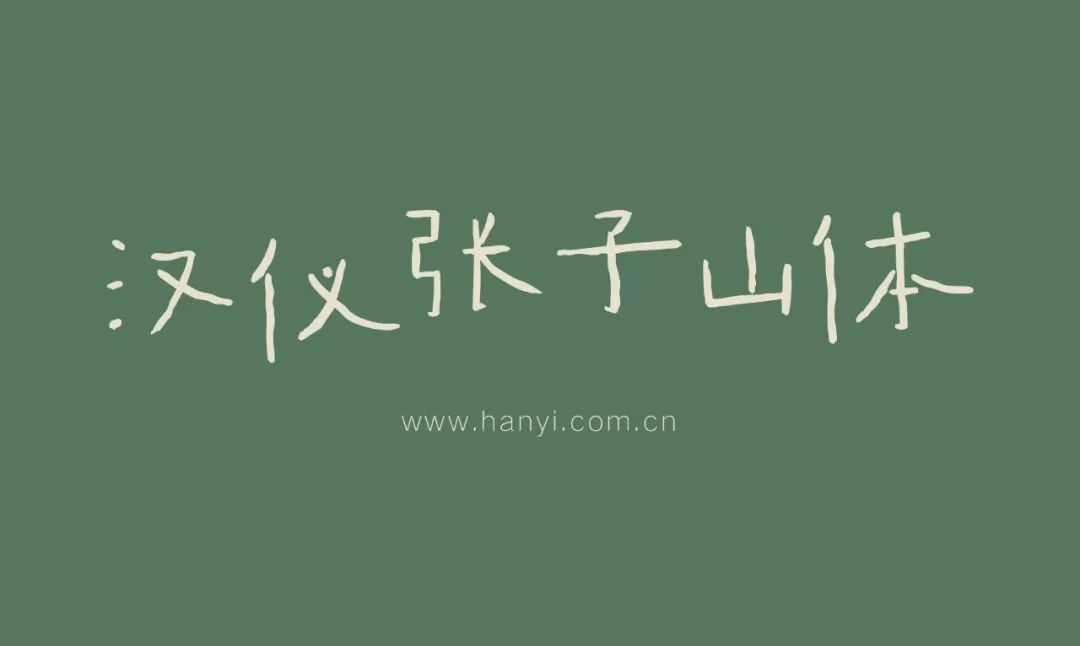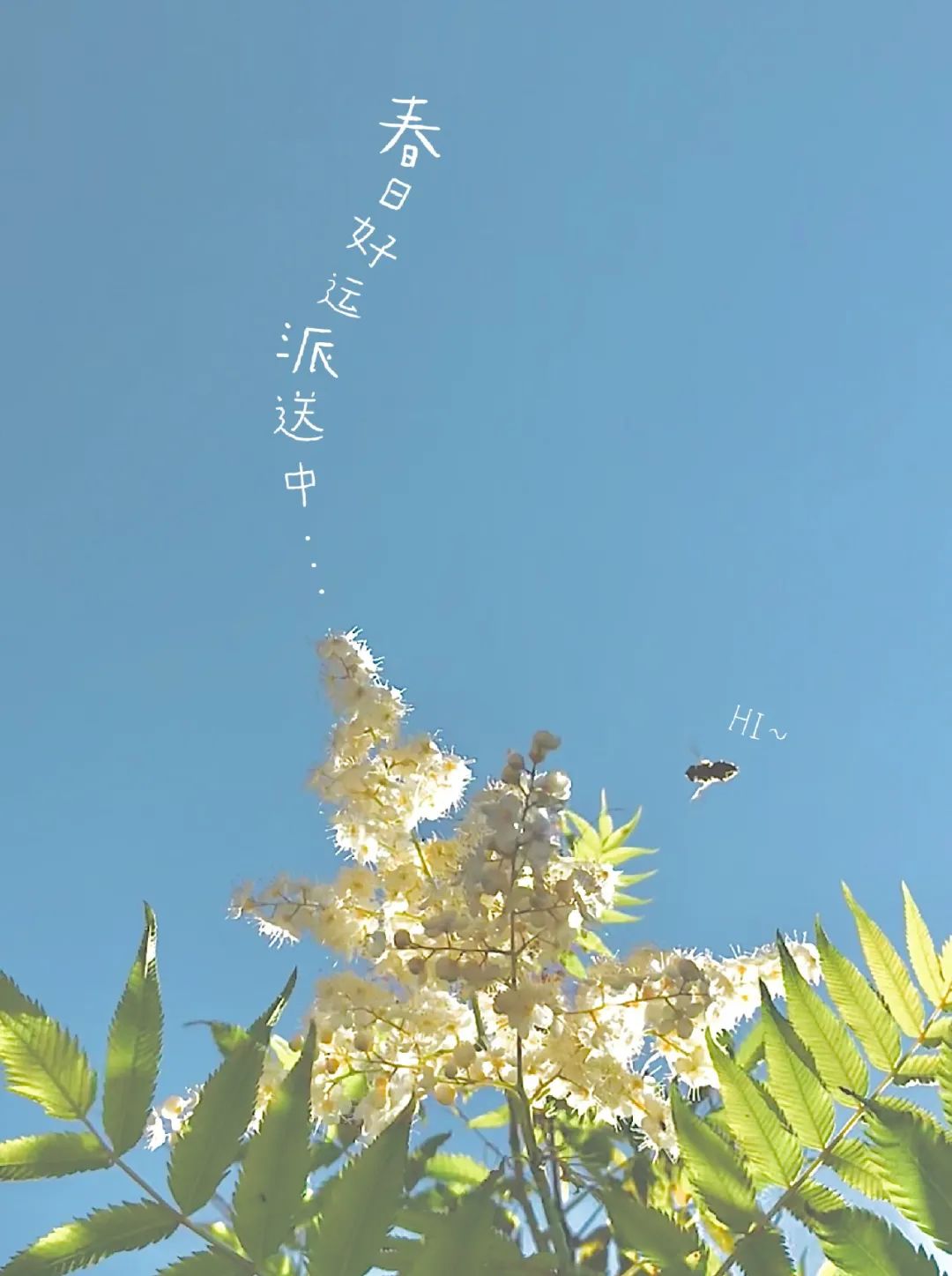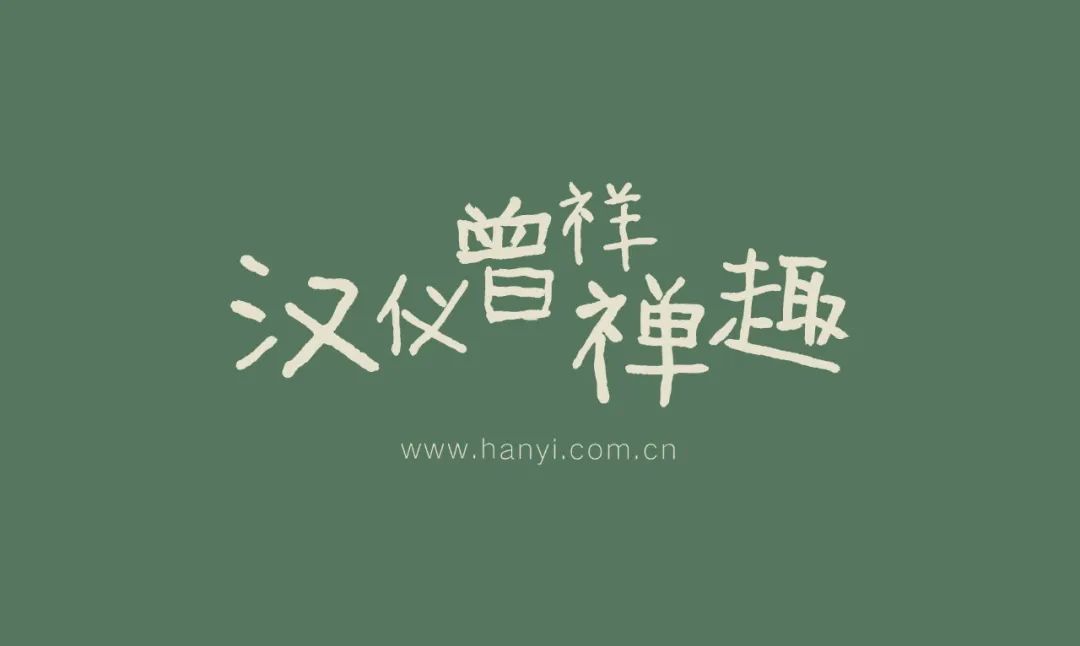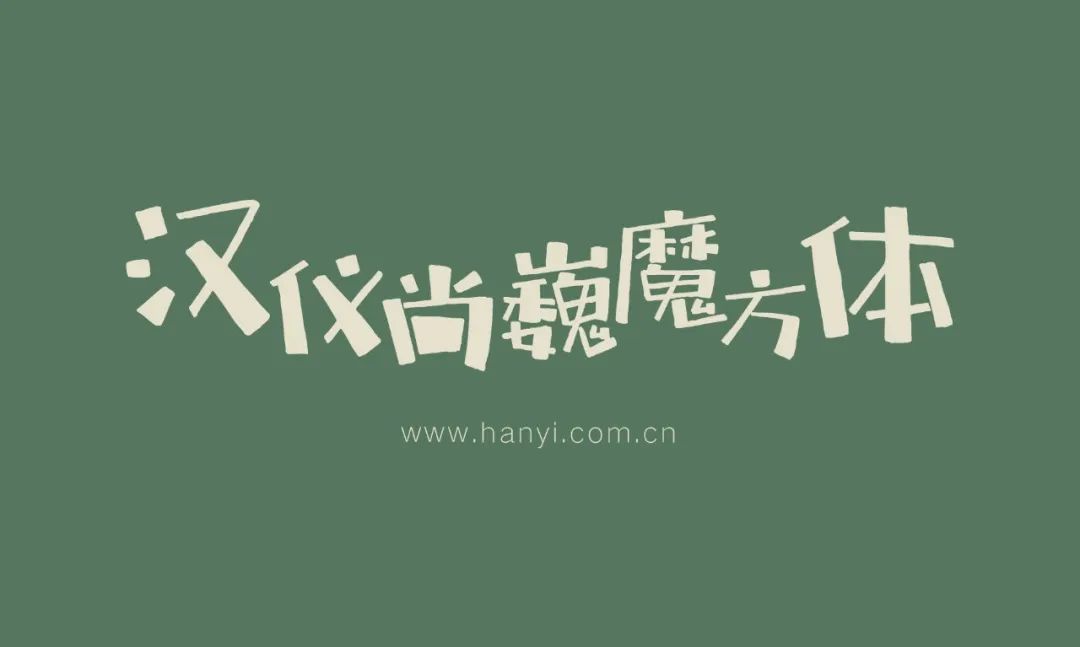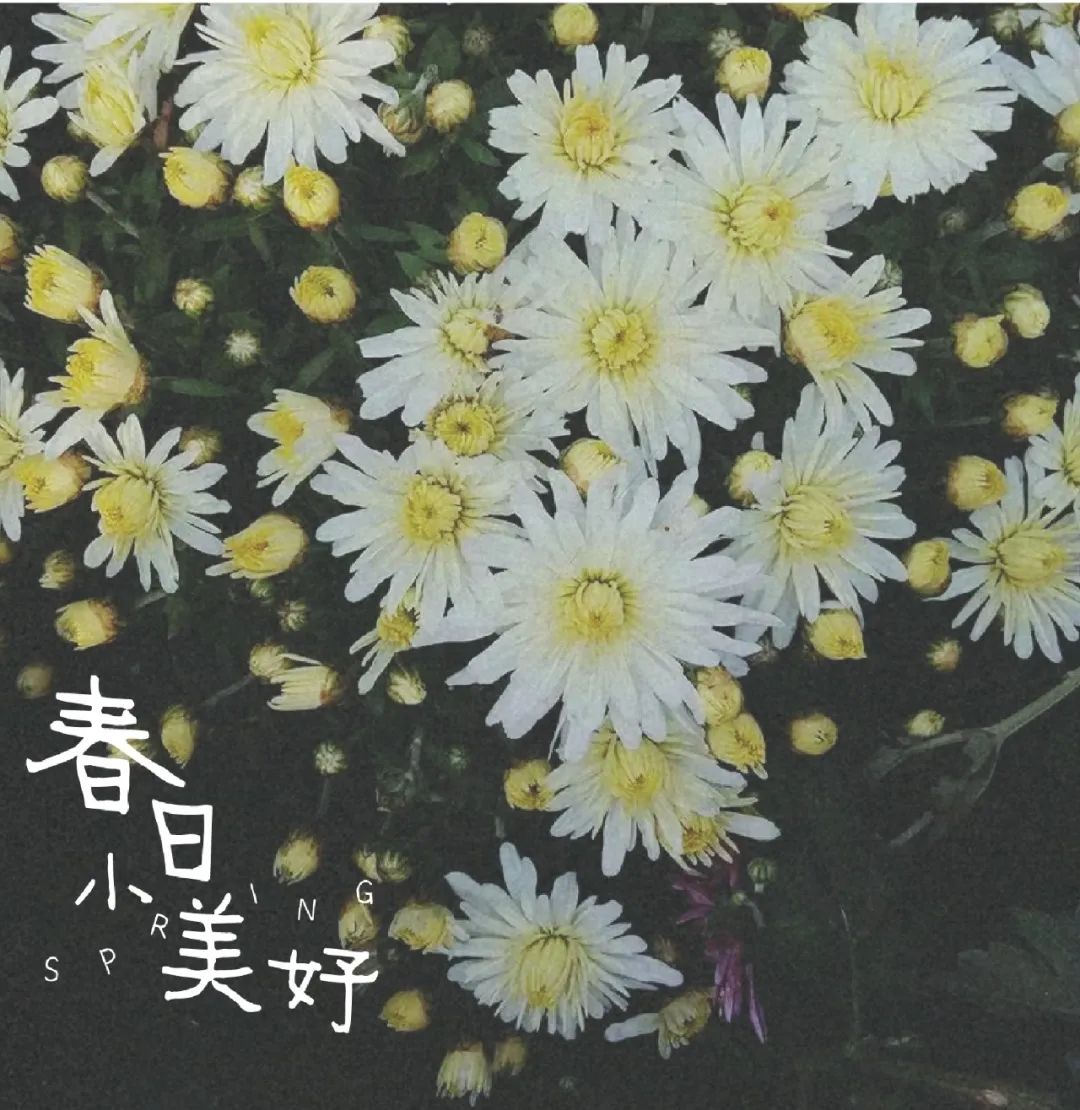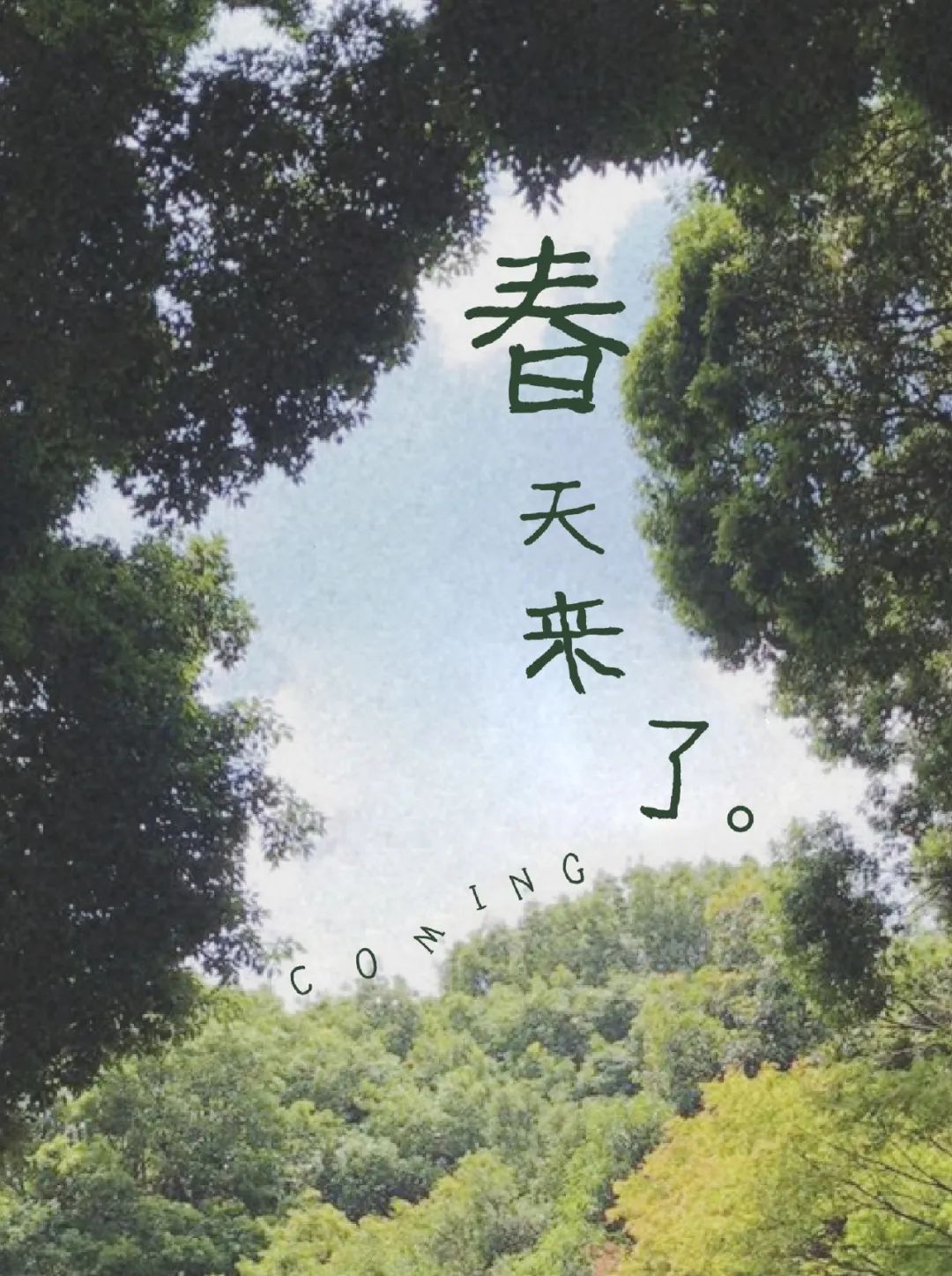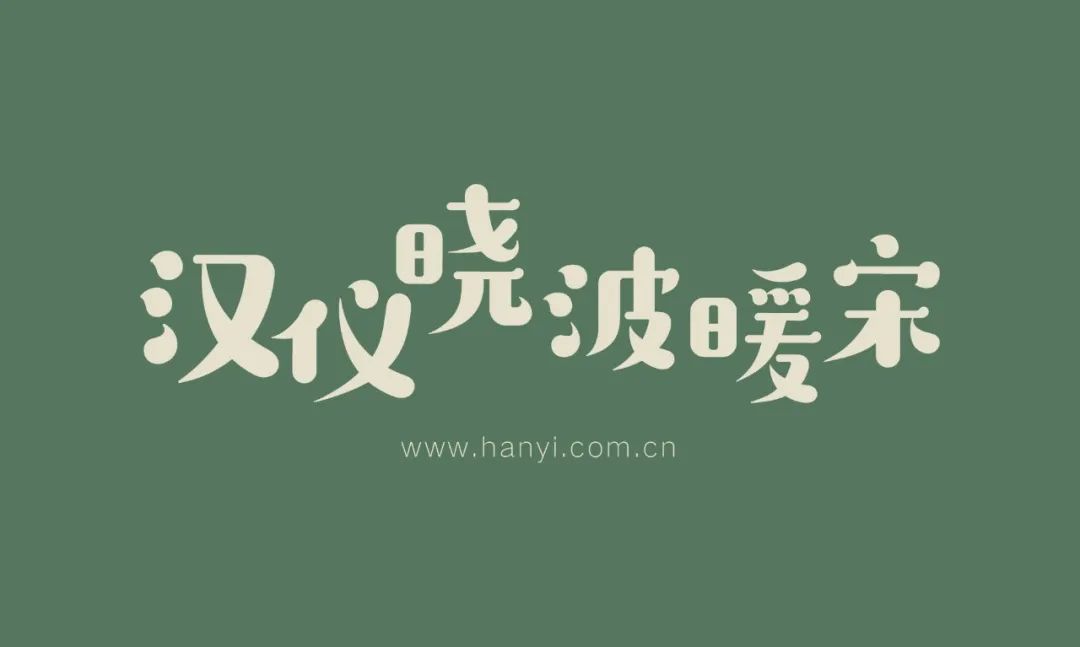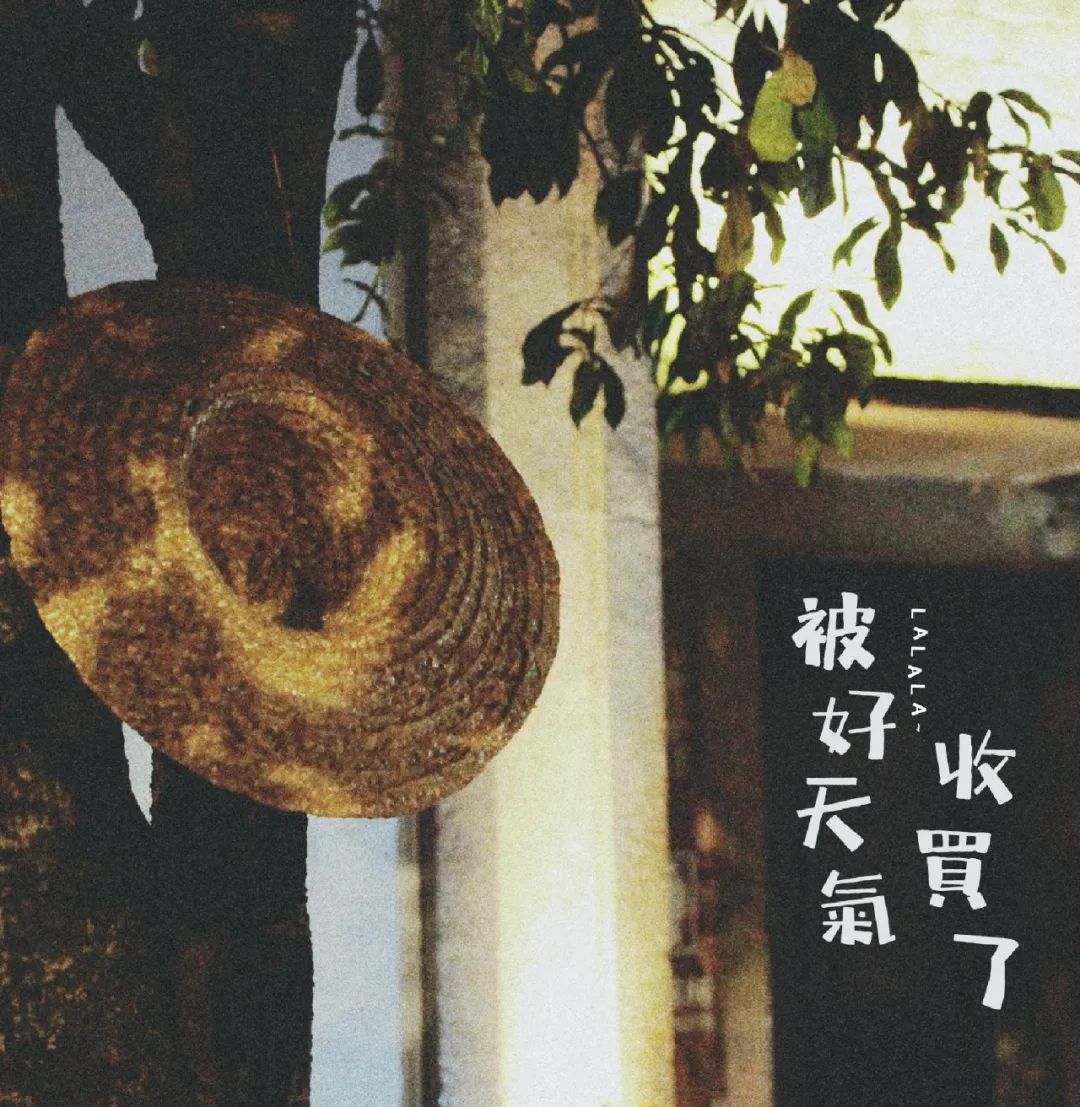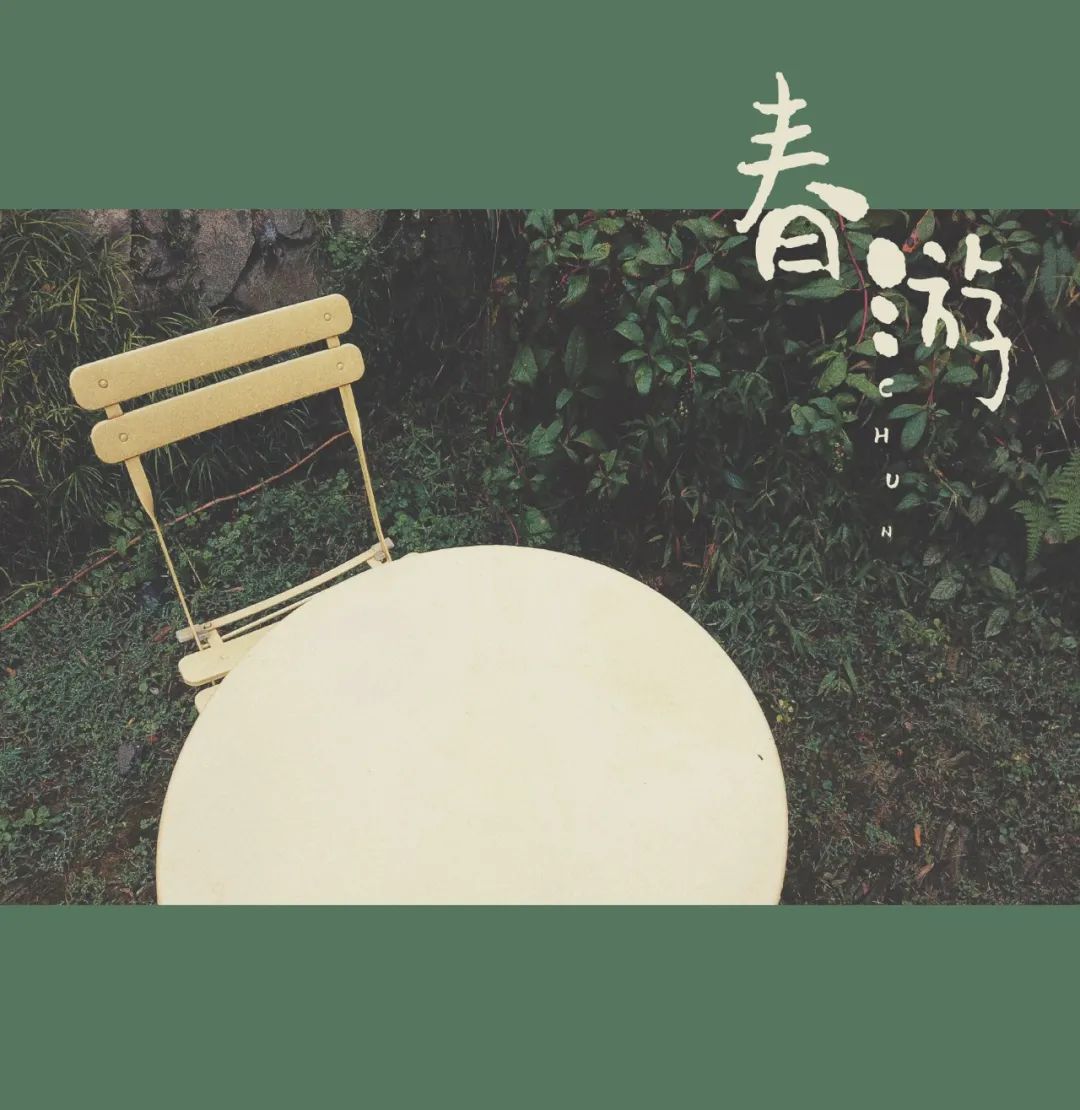
小清晰字体大全,什么字体才能配得上你的小清新气质?
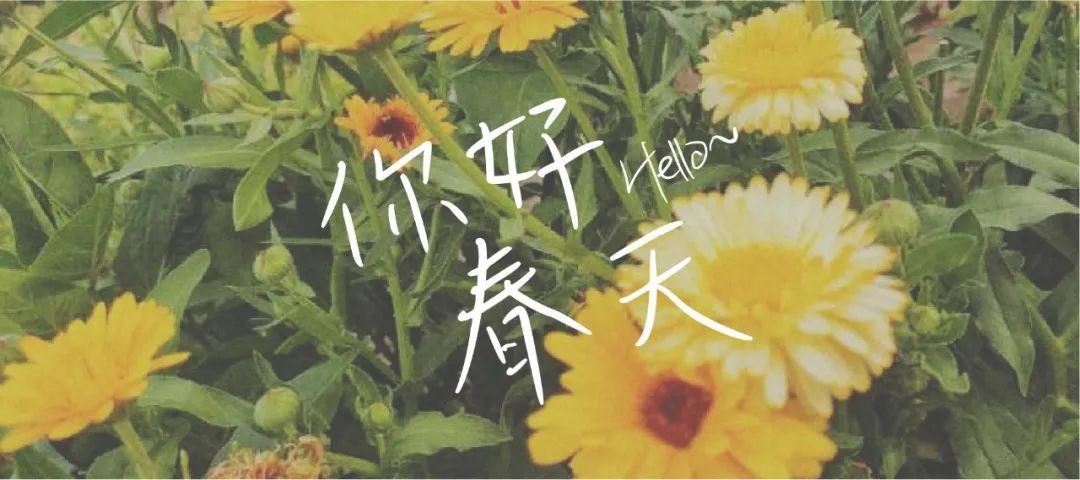
春天来了,
外面犄角旮旯的小花花都开了,
虽然还不能出门远游,
但出去拍一下家门口的小美好还是可以有的。
拍花拍得腿都蹲麻了,
风景怎么样先不说,
但气质这块还是得拿捏得稳稳的。
姨来推荐几款春日气息的字体,
搭配你的小清新气质美炸你票圈,
来和我一起看春暖花开呀!
汉仪张子山体
我来给你派送春日好运啦!
请注意查收!
汉仪曾翔禅趣
青草的香味告诉我,
是春天来了!
汉仪花农体
墙角的小花开了,
也是春日的小美好。
汉仪尚巍魔方体
我的心情已经被好天气收买了!
汉仪尚巍清茶体
想要和你一起春游~
汉仪新蒂芳草体
看,
是春天的味道!
汉仪字研欢乐宋
有花开的地方,
就让人感到快乐!
汉仪晓波暖宋
春风十里,
也吹不动你。
(等等,好像画风不太一样...)
春风十里不如你!
愿大家能够早日出游,
享受美好的天气!